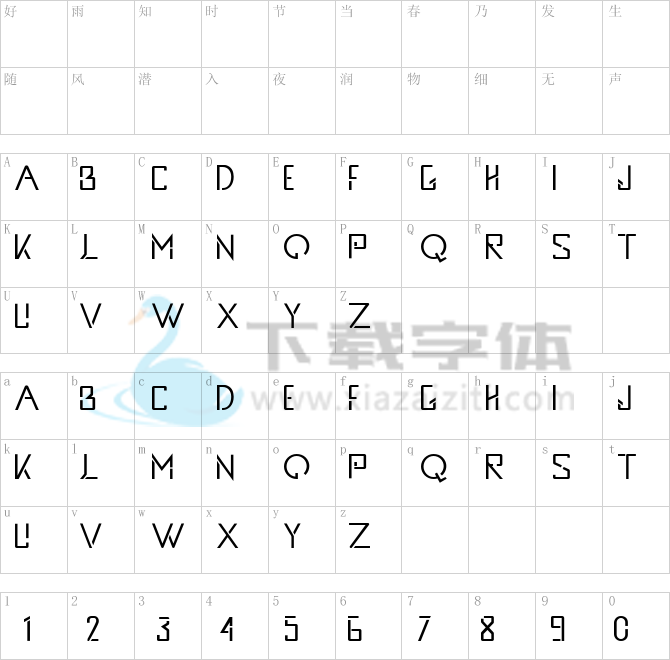
Andromeda.ttf字体下载,这款字体结构工整、笔画清晰,兼顾美观与易读性,适用于标题、正文、海报、包装、LOGO 等多种场景。字形优雅稳定,风格百搭耐看,适配日常排版与创意设计,让文字呈现更舒适、更具质感。Andromeda.ttf字体下载一笔一画,皆是细节,以均衡的比例、流畅的线条打造舒适视觉体验,字形端正大气,风格简约现代。无论是商业设计、品牌宣传还是日常排版,都能轻松驾驭,让文字更有格调与力量。Andromeda.ttf字体下载字体下载。